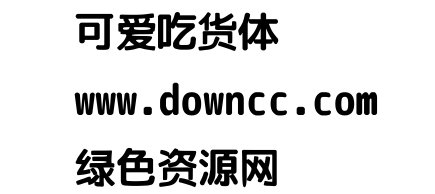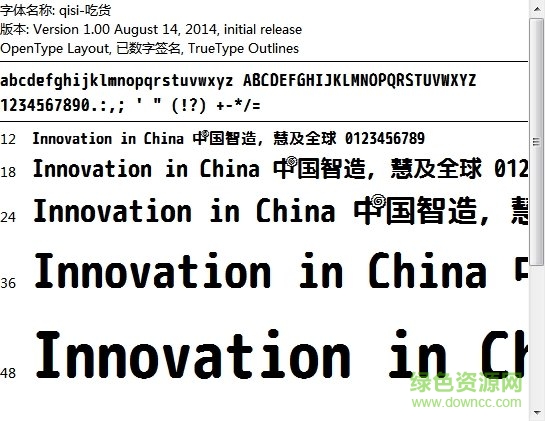
吃貨體是一款可以特色裝飾的可愛(ài)卡通字體,整體造型自帶加粗加黑設(shè)計(jì),顯得更為醒目嚴(yán)謹(jǐn),讓文字更加深入人心,有著十分活潑的生動(dòng)體驗(yàn),喜歡的朋友就來(lái)綠色資源網(wǎng)收集使用吧!
吃貨字體是一款以粗圓體為原形的手機(jī)字體。在字體體間加入了卡通水果的圖案進(jìn)行裝飾,增加了趣味感,可以運(yùn)用在平面設(shè)計(jì)、藝術(shù)設(shè)計(jì)等多種場(chǎng)合。